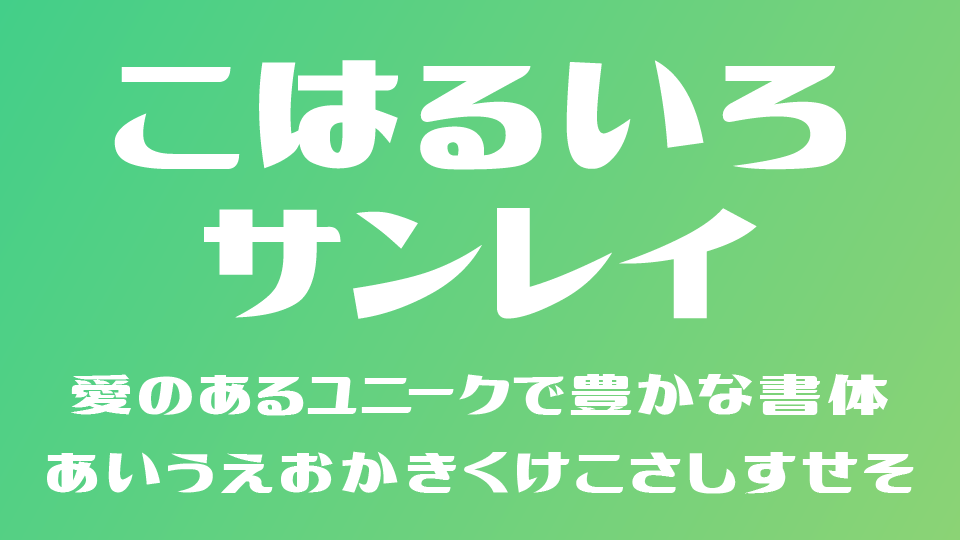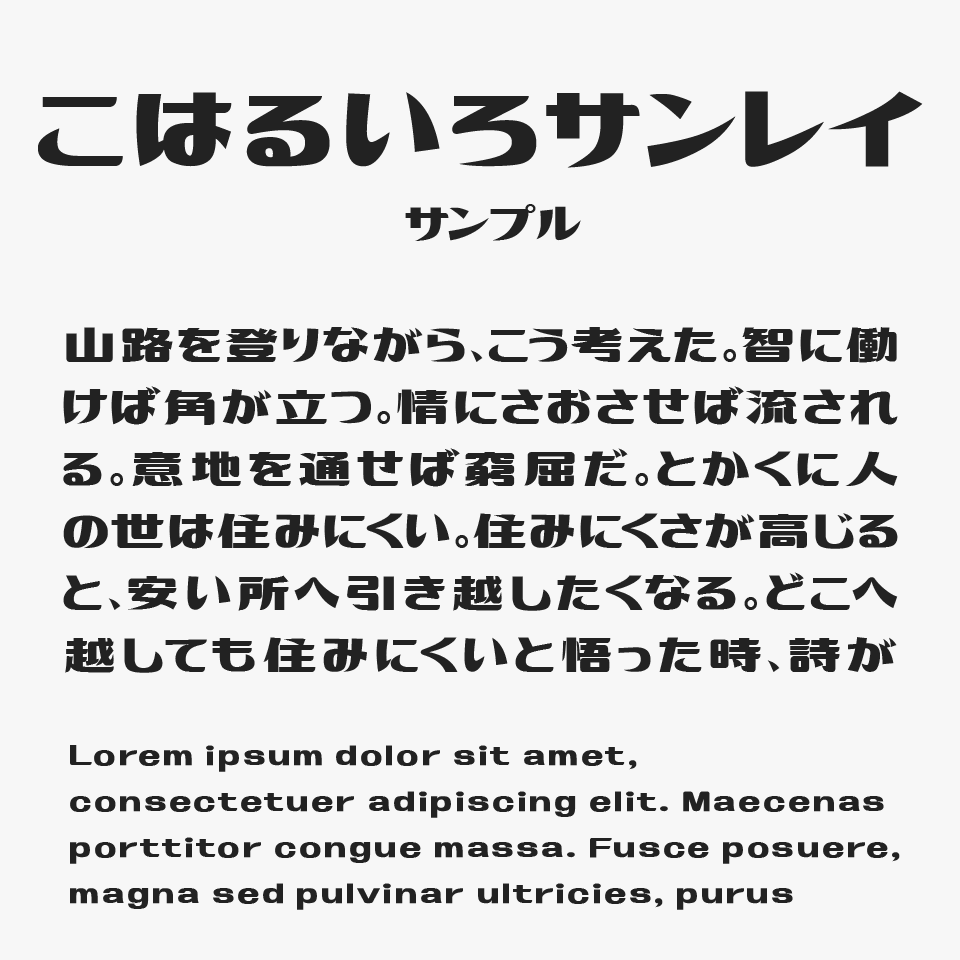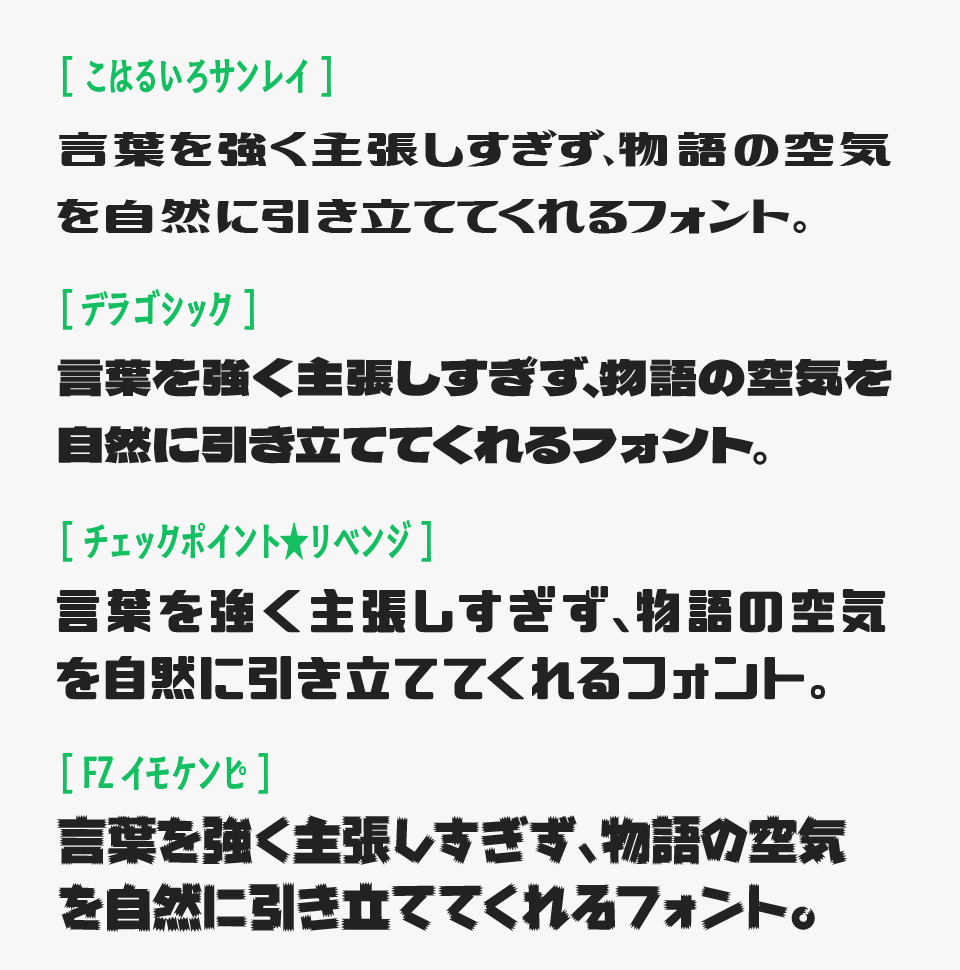
こはるいろサンレイ
こはるいろサンレイは、きんいろモザイクのロゴの「ハロー!!」を文字ををモチーフに制作された デザインフォントです。
アニメ内の文字をモチーフにフォントしているところが少しユニークで面白い取り組みですよね。フォントもユニークなフォルムがポップで可愛らしい印象なので、アニメ系デザイン以外でも子供向けなどのカワイらしいデザインとの相性とても良さそうです。
横に大きく広がった平体シルエットと、しっかりとした太さが特徴的なフォントです。そのため、小さなサイズでは文字が潰れて見えやすいので、ロゴやタイトル、見出しなど、大きめのサイズで使用すると魅力をより引き出すことができます。
こはるいろサンレイを、可愛らしいな雰囲気を持つフォントと比較してみると、派手に目立つというよりも、見ている人に安心感や親しみを与えてくれるような、やわらかな空気感が特徴のフォントです。
比較フォントは、「デラゴシック」「チェックポイントリベンジ」「イモケンピ」と使用していますが、どれも特徴的なデザインフォントなので、ぜひあわせてチェックしてみてください。
収録文字は、カタカナ・数字・一部記号・ひらがな・アルファベット・罫線と漢字3351文字が収録されています。